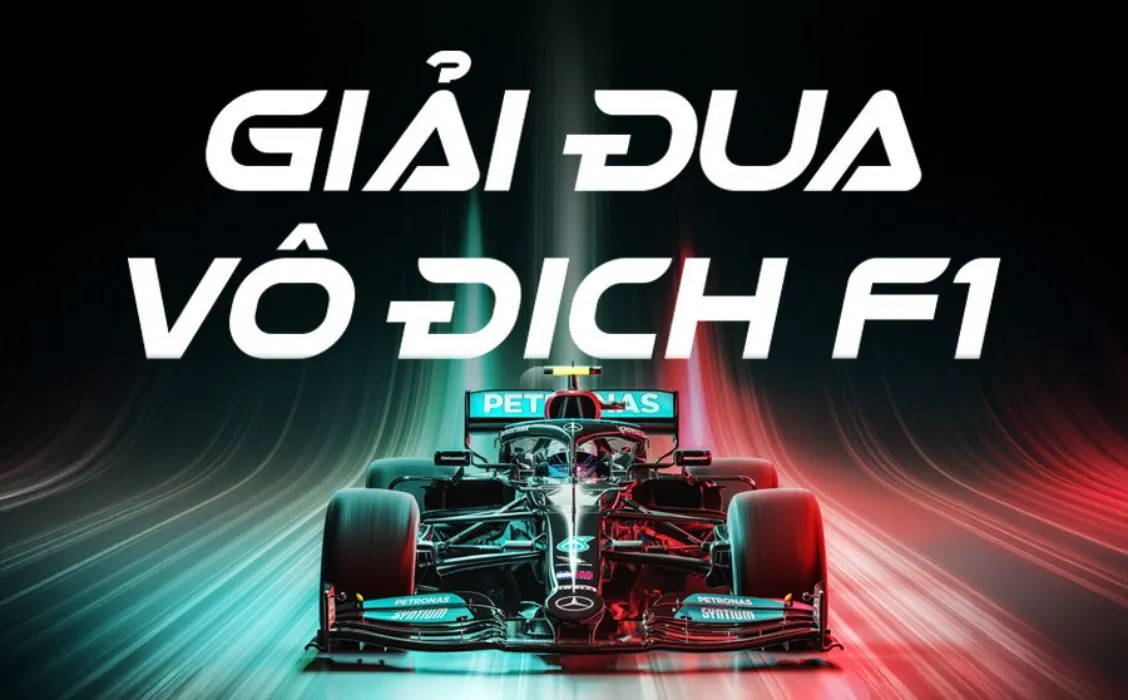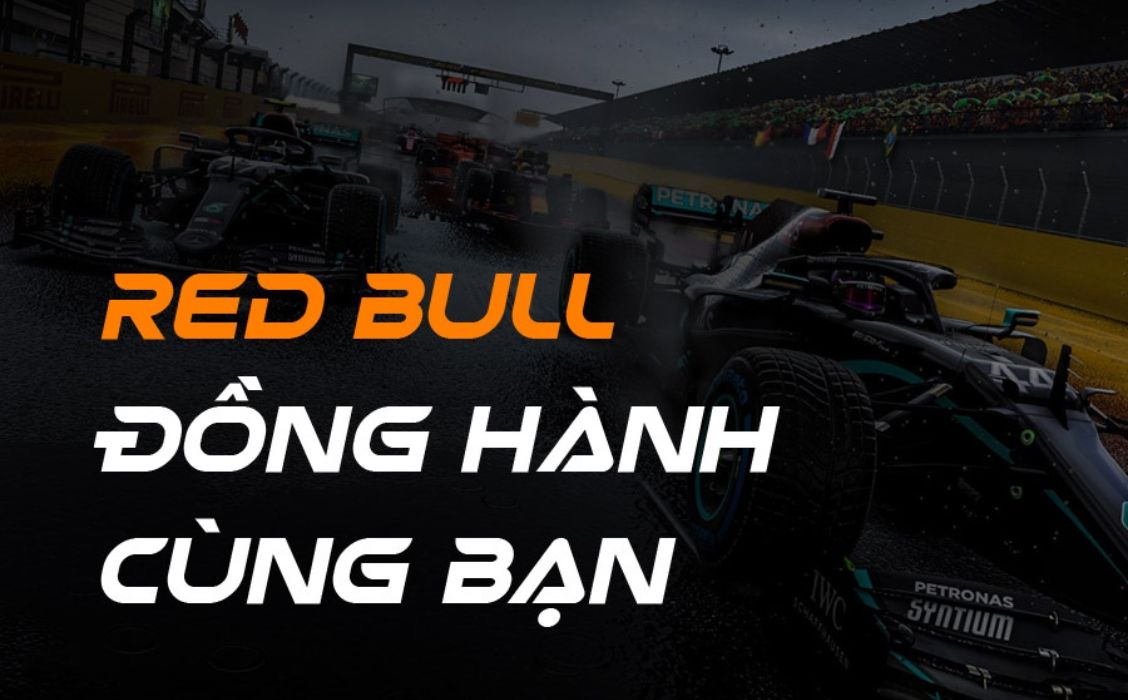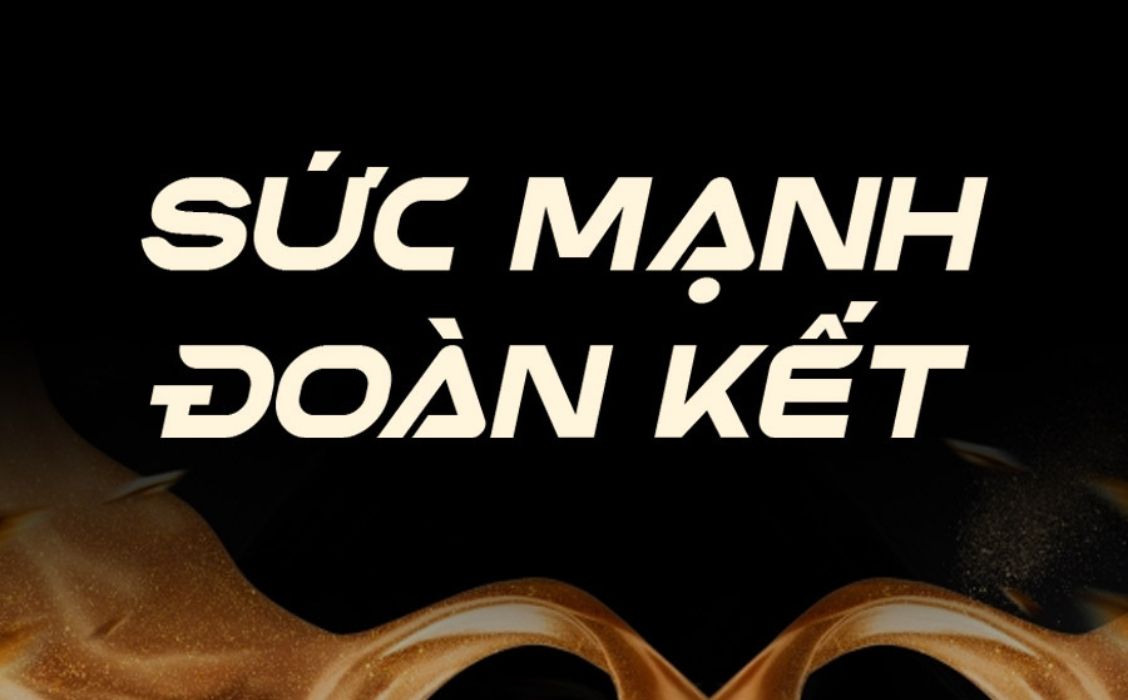
Font chữ thể thao mang phong cách tương lai TH Geardive là lựa chọn nổi bật dành cho các thiết kế cần sự mạnh mẽ, hiện đại và giàu năng lượng. Với đường nét góc cạnh, dứt khoát cùng tinh thần công nghệ rõ nét, TH Geardive mang đến cảm giác tốc độ, bứt phá và cá tính, rất phù hợp với các chủ đề thể thao, game, eSports, công nghệ và poster sự kiện hiện đại.
Kiểu chữ này gây ấn tượng nhờ phong cách futuristic độc đáo, giúp tiêu đề trở nên nổi bật, cuốn hút và chuyên nghiệp hơn. Font phù hợp để sử dụng trong thiết kế logo, banner, áo thể thao, poster quảng cáo, thumbnail video, bìa ấn phẩm hoặc các sản phẩm truyền thông cần điểm nhấn thị giác mạnh.
TH Geardive không chỉ mang tinh thần thể thao năng động mà còn tạo cảm giác mới mẻ, sáng tạo và khác biệt cho tổng thể thiết kế. Đây là lựa chọn phù hợp cho designer, nhà sáng tạo nội dung và thương hiệu đang tìm kiếm một font chữ ấn tượng, đậm chất tương lai và dễ ứng dụng trong nhiều phong cách thiết kế khác nhau.